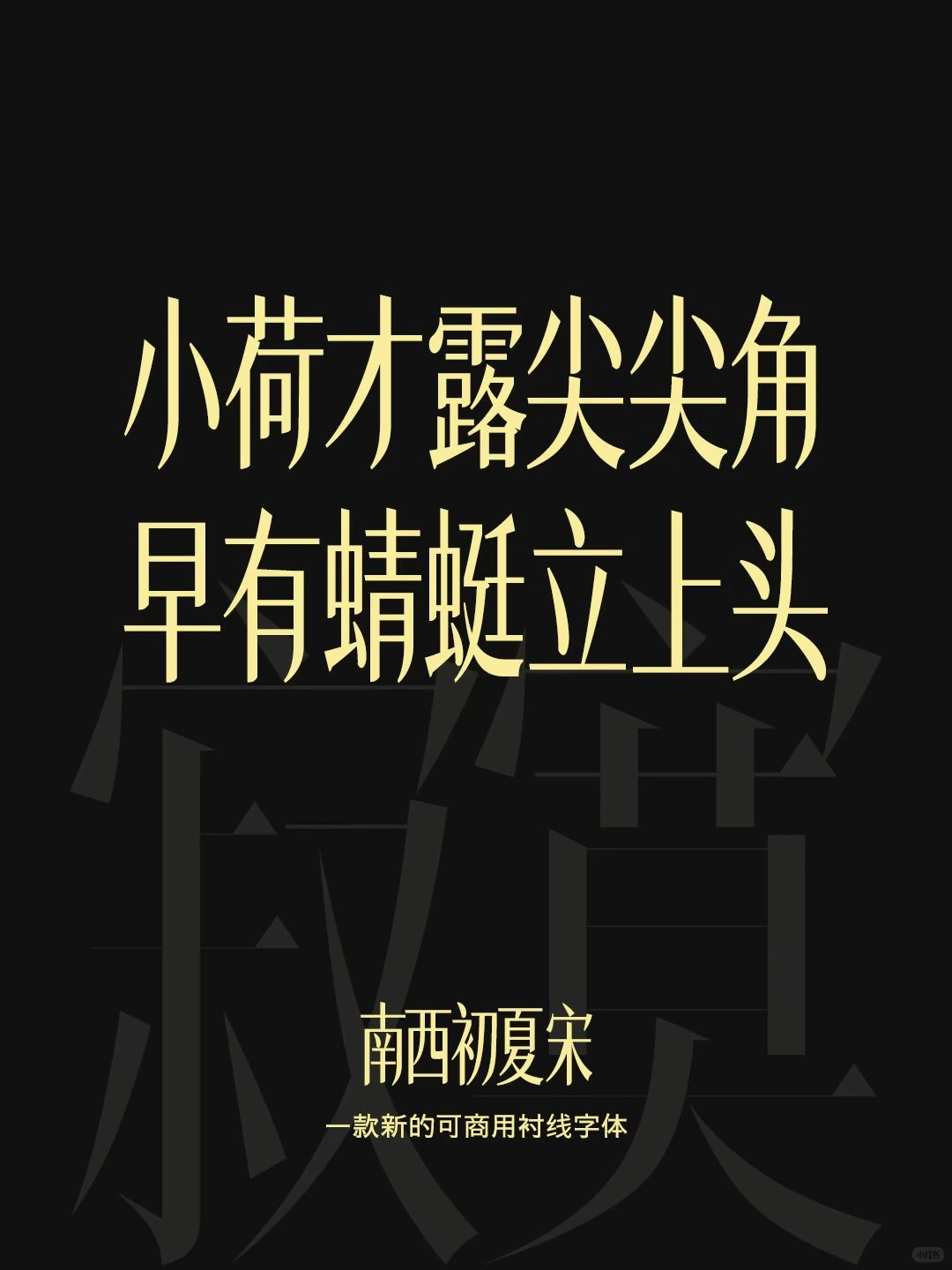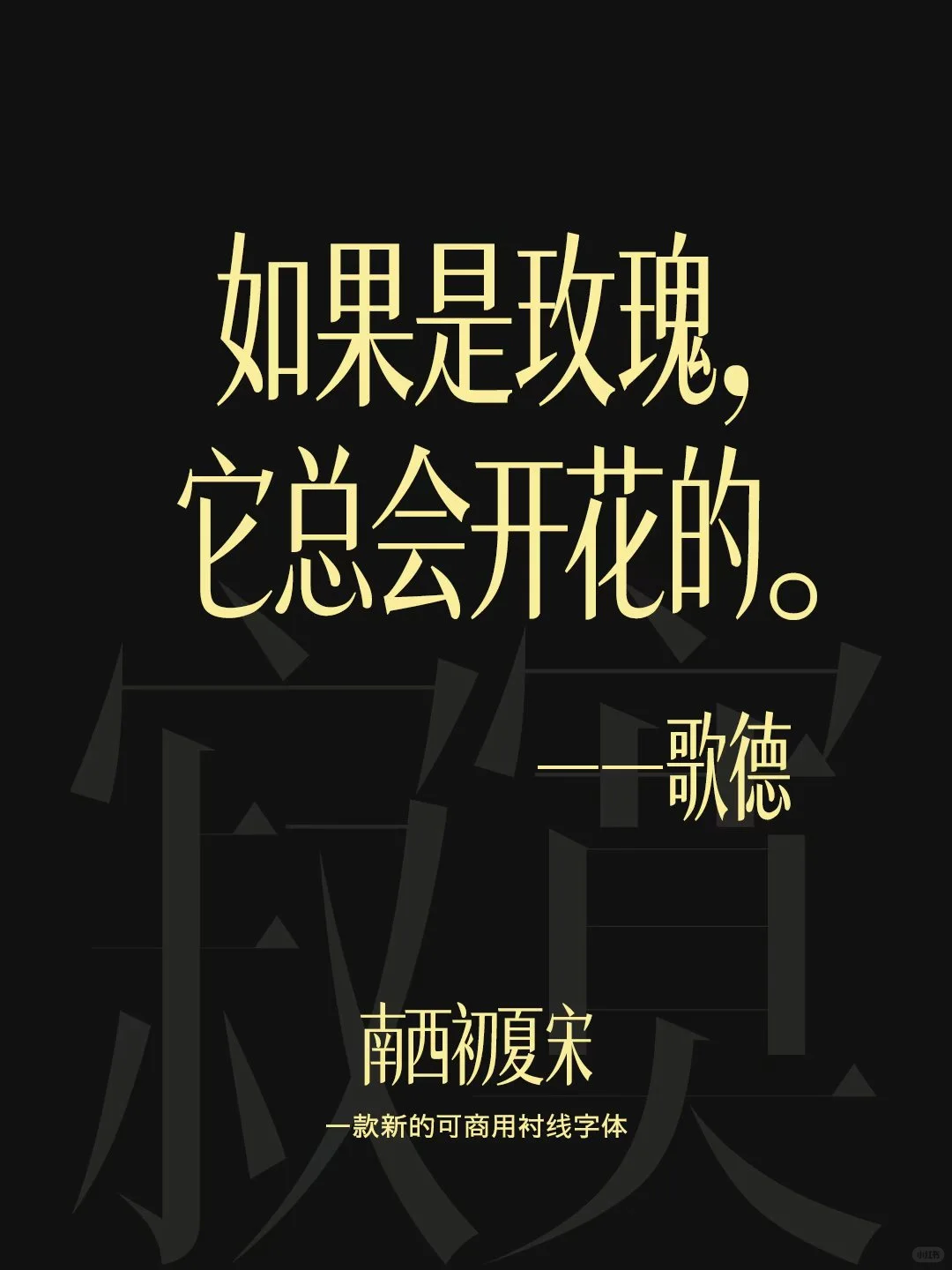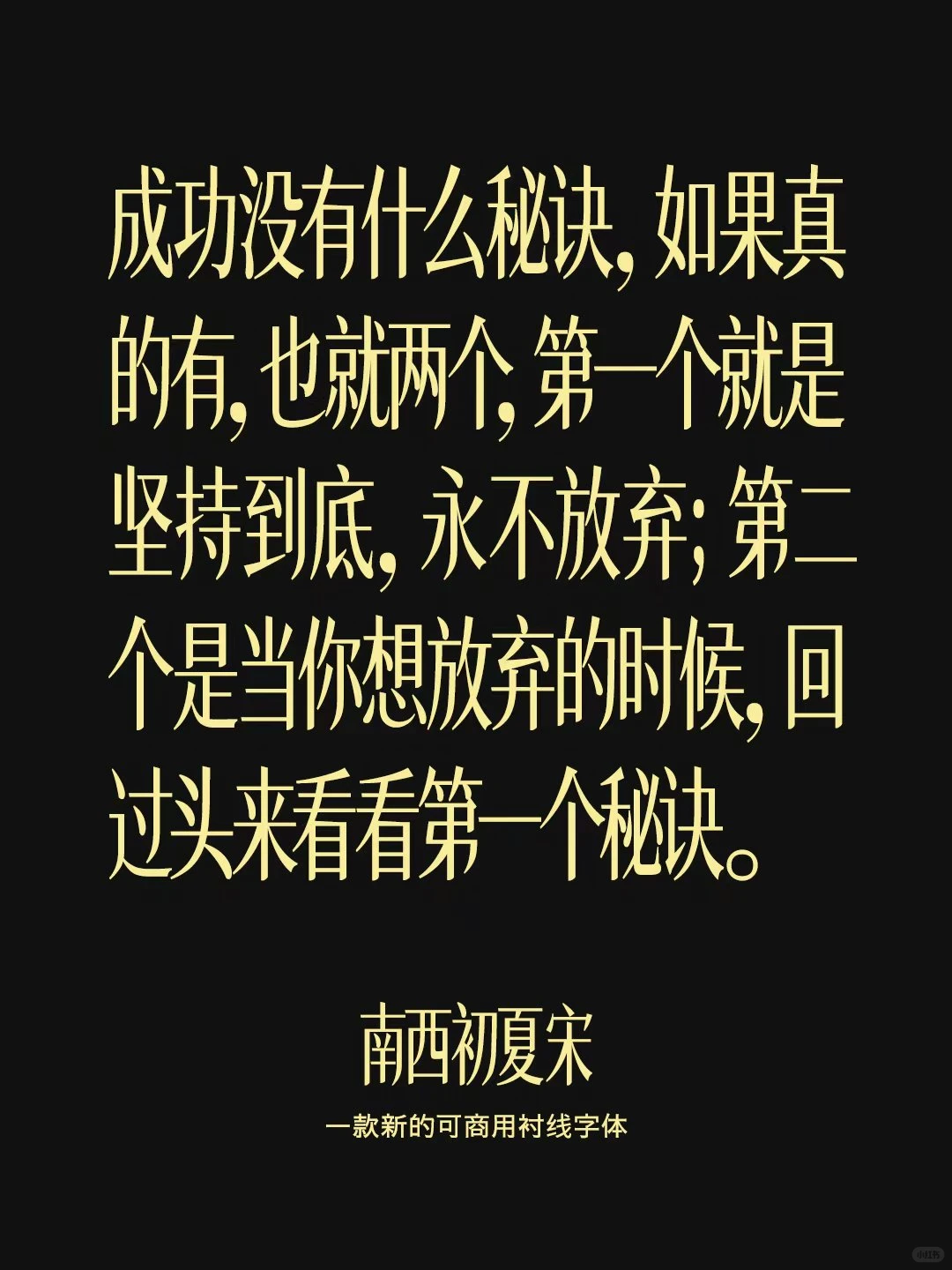
南西初夏宋是松陵南西创作的一款基于思源宋体的商用衬线字体。思源宋体作为基础,因其广受欢迎和出色的字形设计,为这款字体提供了坚实的框架。设计师在此基础上,加入了一些非常个人化和精细的调整,这些调整让南西初夏宋在保持经典韵味的同时,显得更加独特。 最明显的特征在于横笔的末端,会带有一个非常微妙、自然上扬的弧度。这个弧度的设计,经过了设计师的细致打磨,既不过分突兀,也不显得生硬,仿佛是手写过程中自然形成的笔触。这种收笔处理,一方面完整地承袭了经典宋体那种结构严谨、端庄大方的气质,让文字在传统场景中依然保持稳重感。 另一方面,正是这个小小的弧线设计,为原本规整的字体注入了一抹仿佛亲手书写般的流动感和亲切温度。它让静态的文字仿佛有了动态的生命力,读起来更加柔和自然。在实际使用中,无论是用于书籍排版还是屏幕显示,南西初夏宋都能让文字看起来既稳定又生动,增强了整体的视觉吸引力和阅读舒适度。